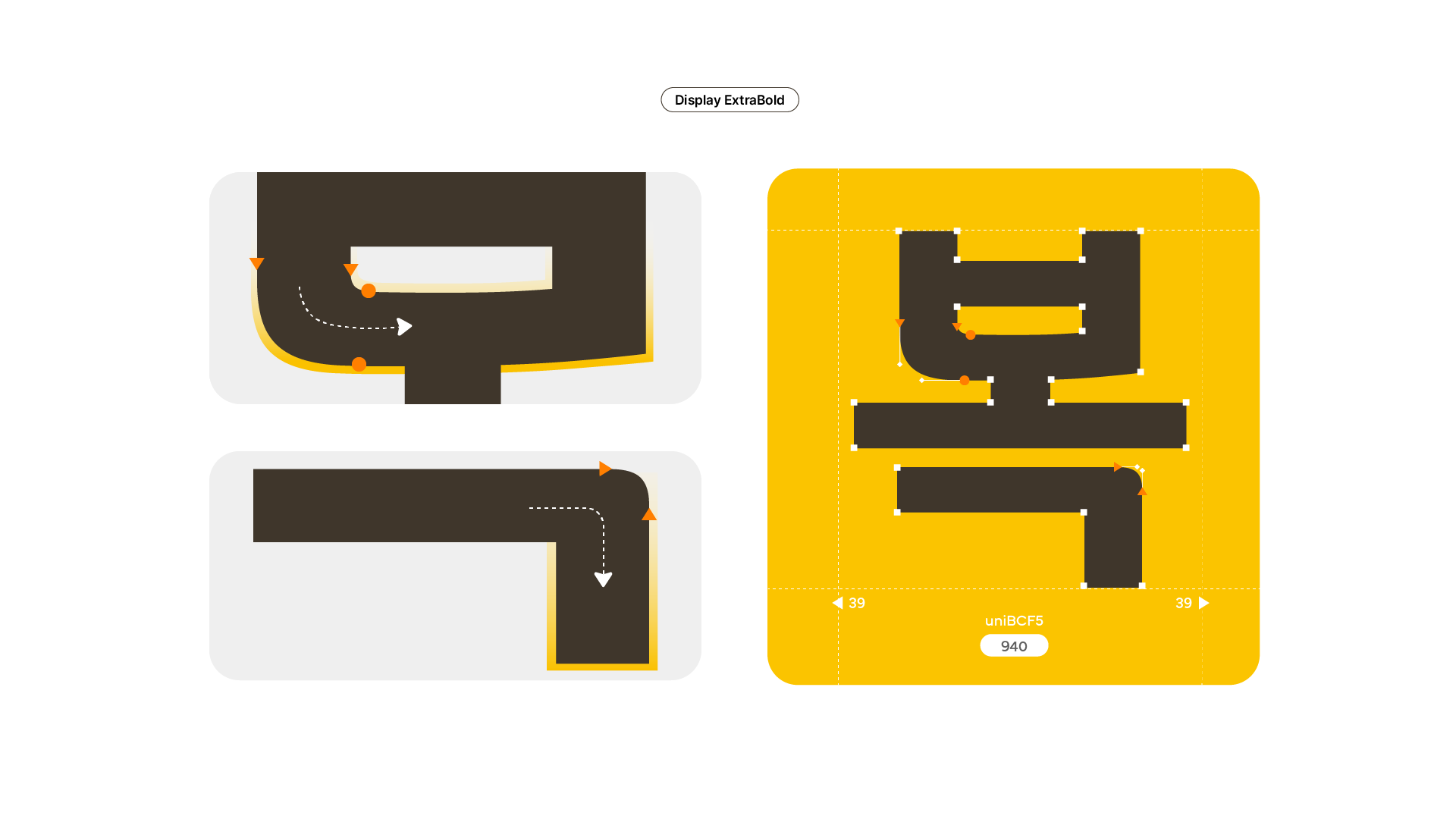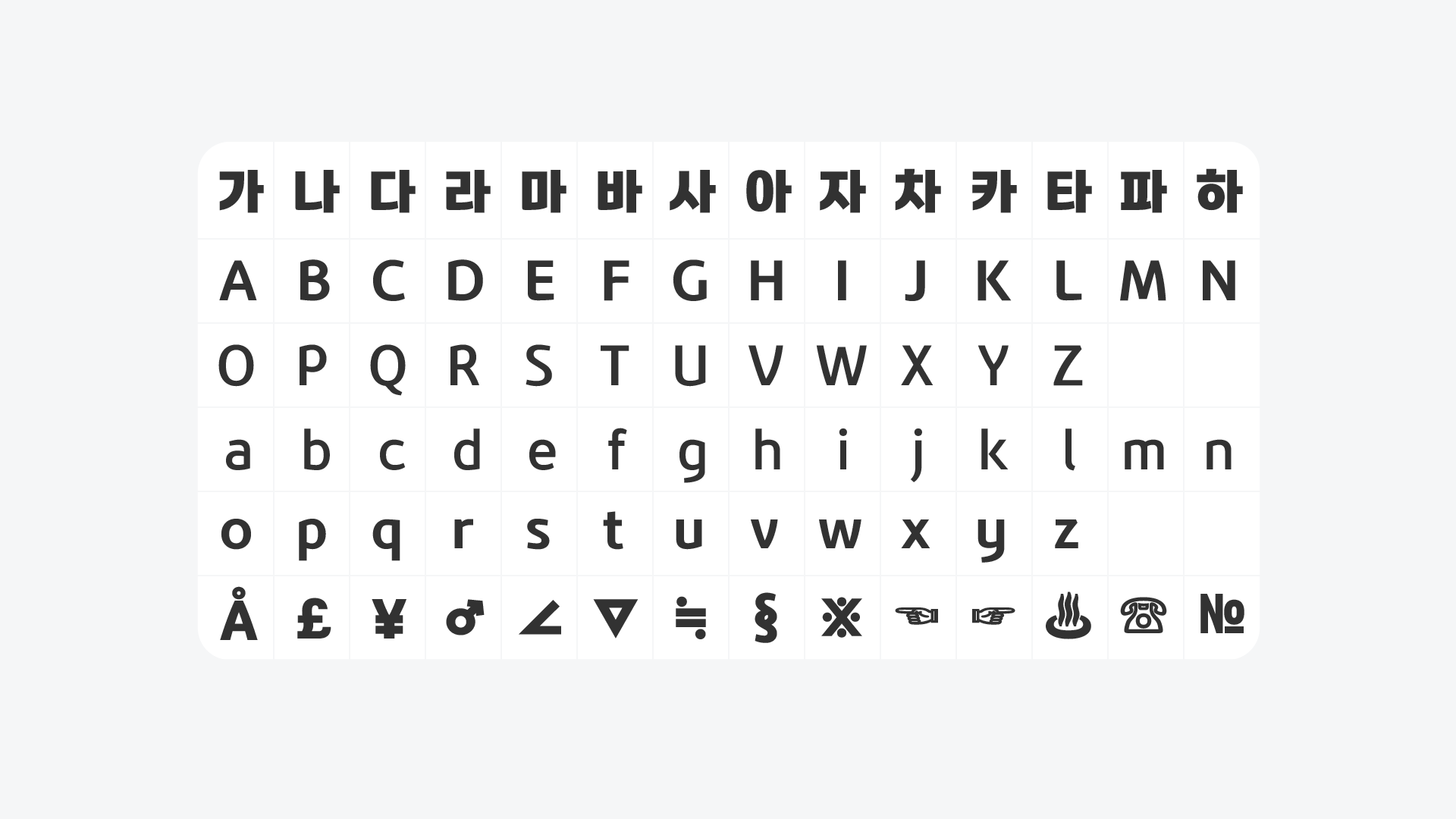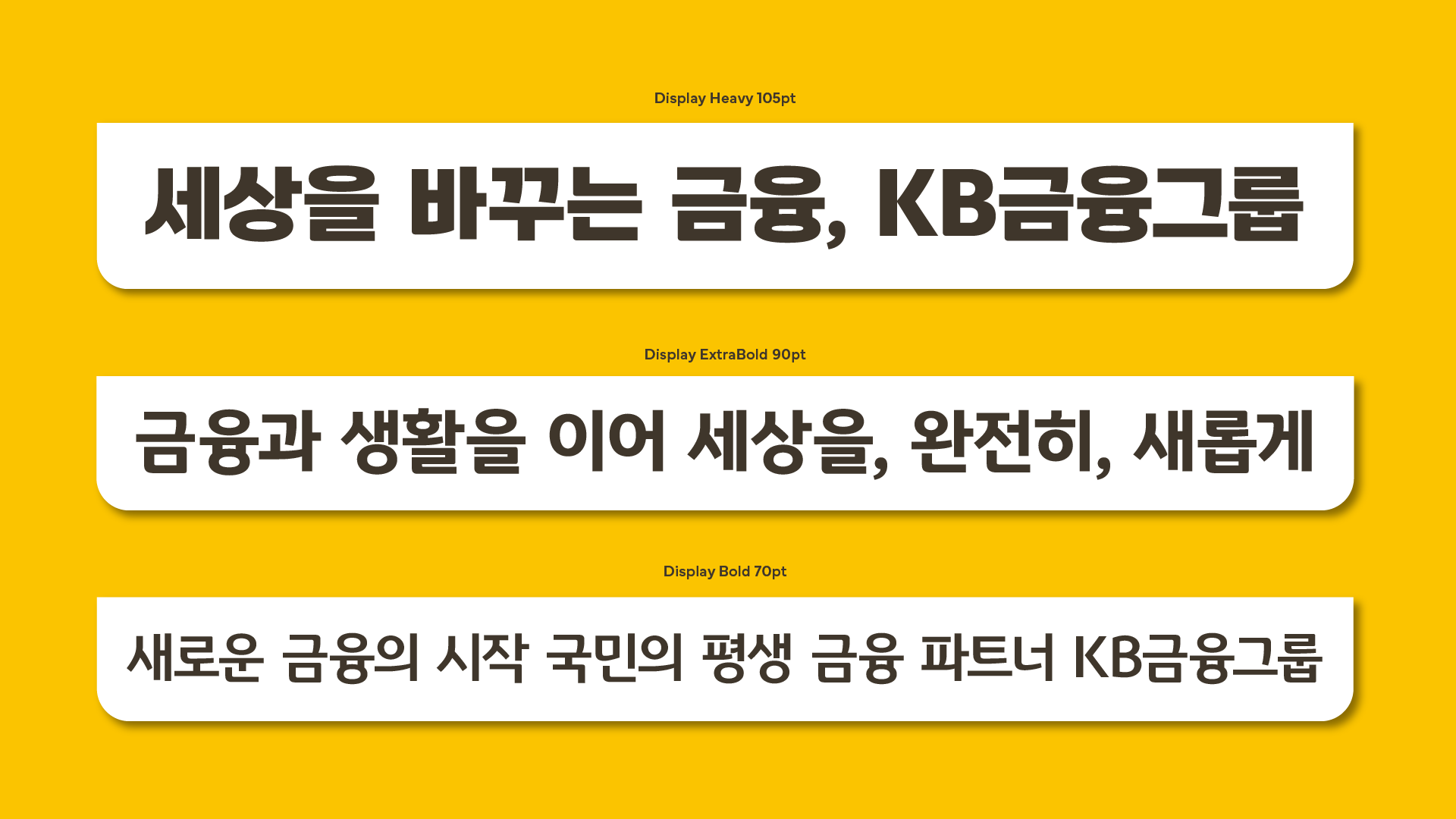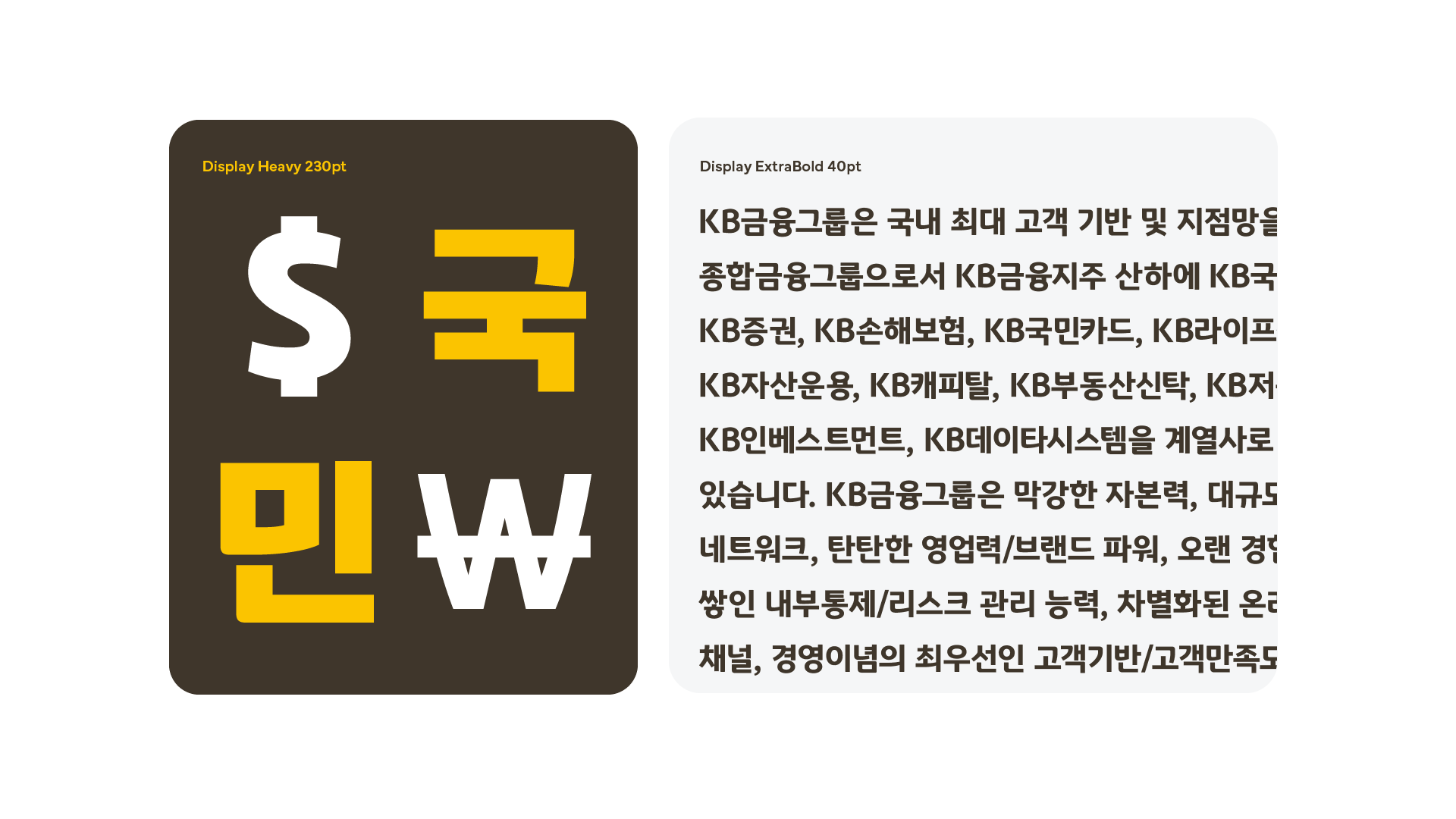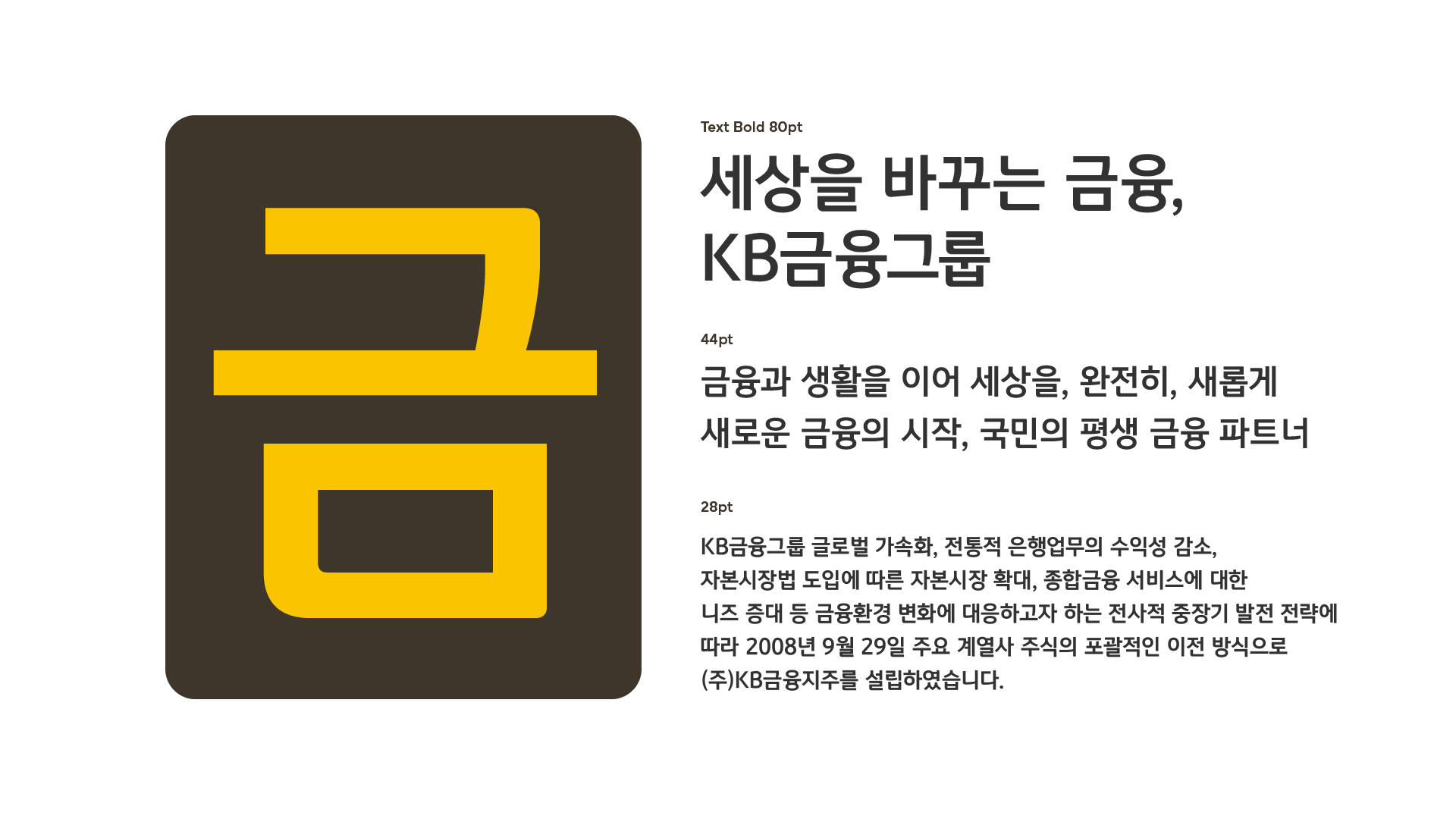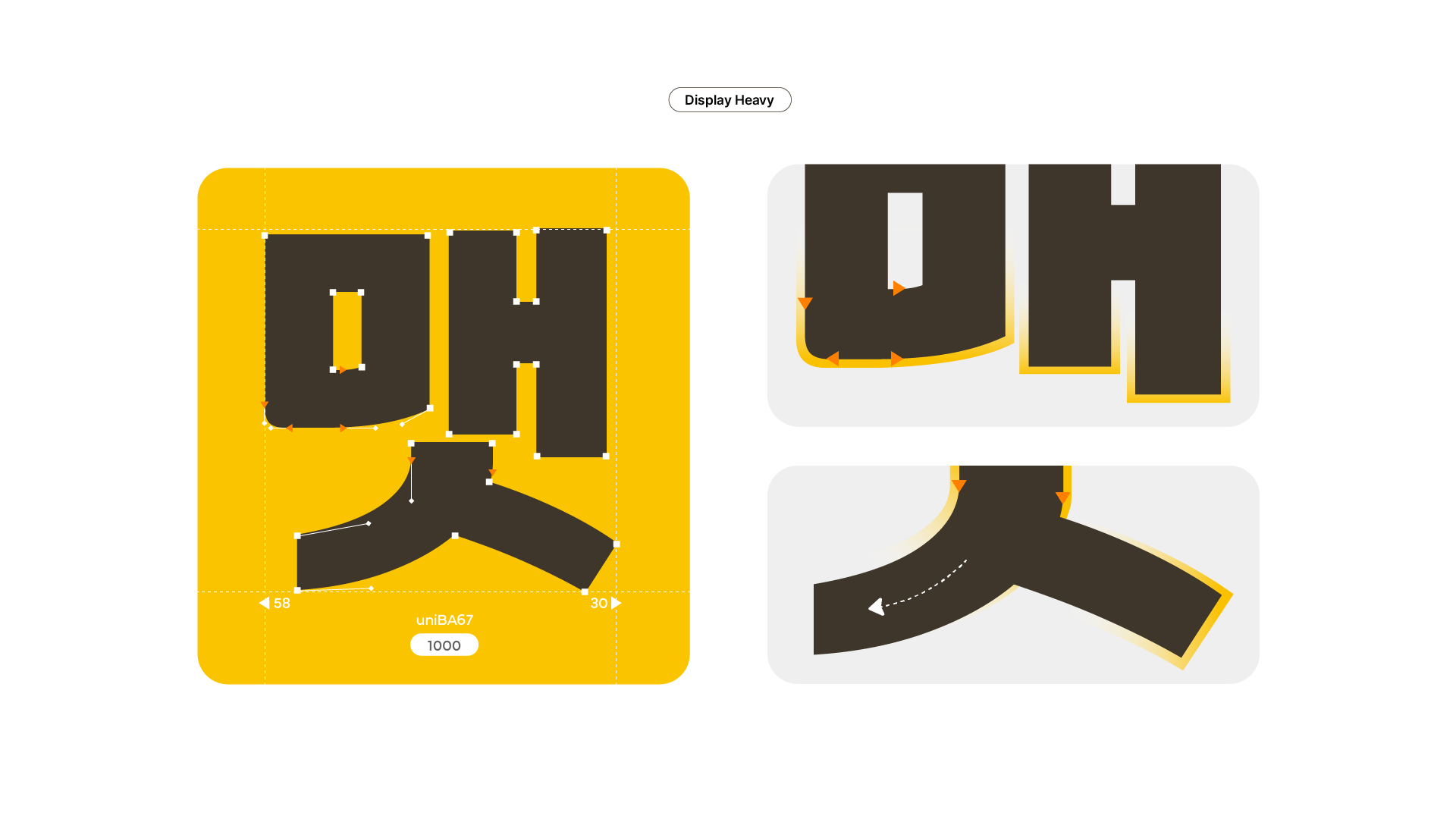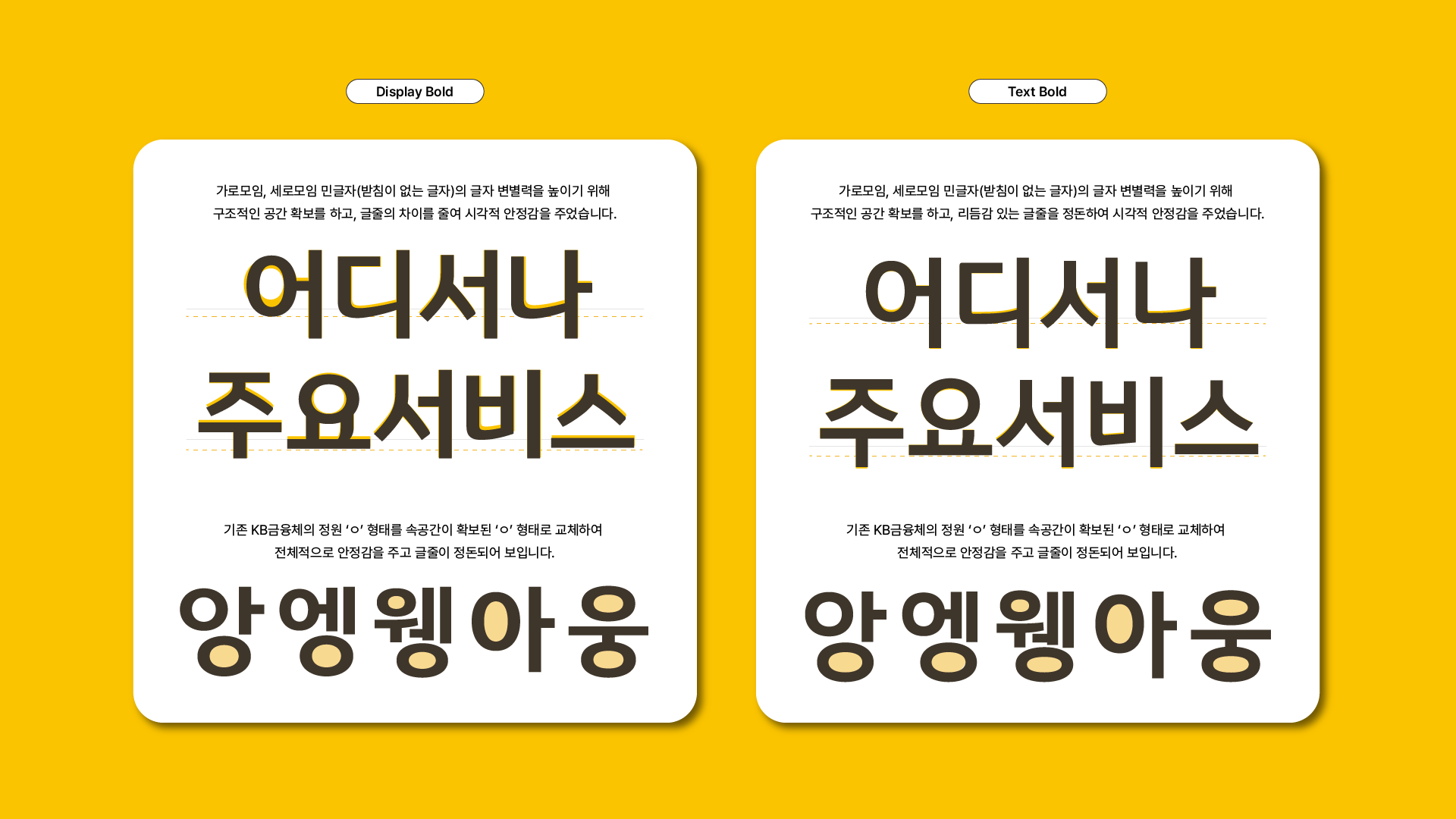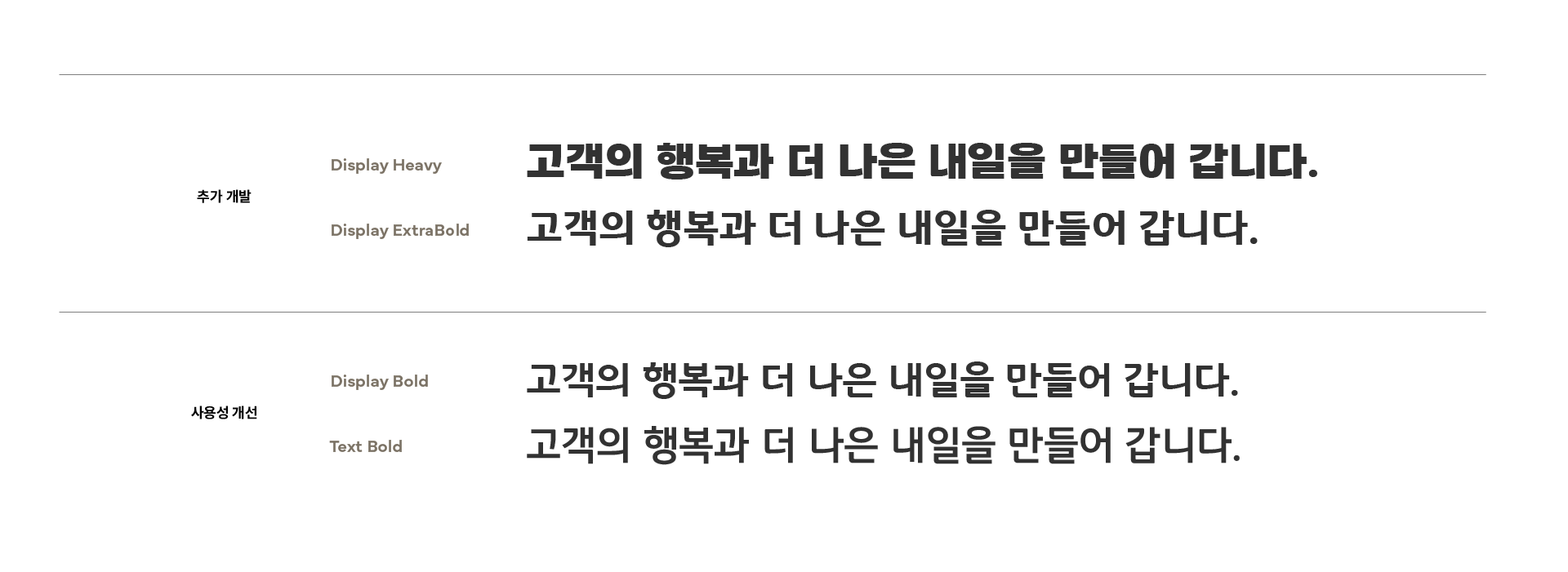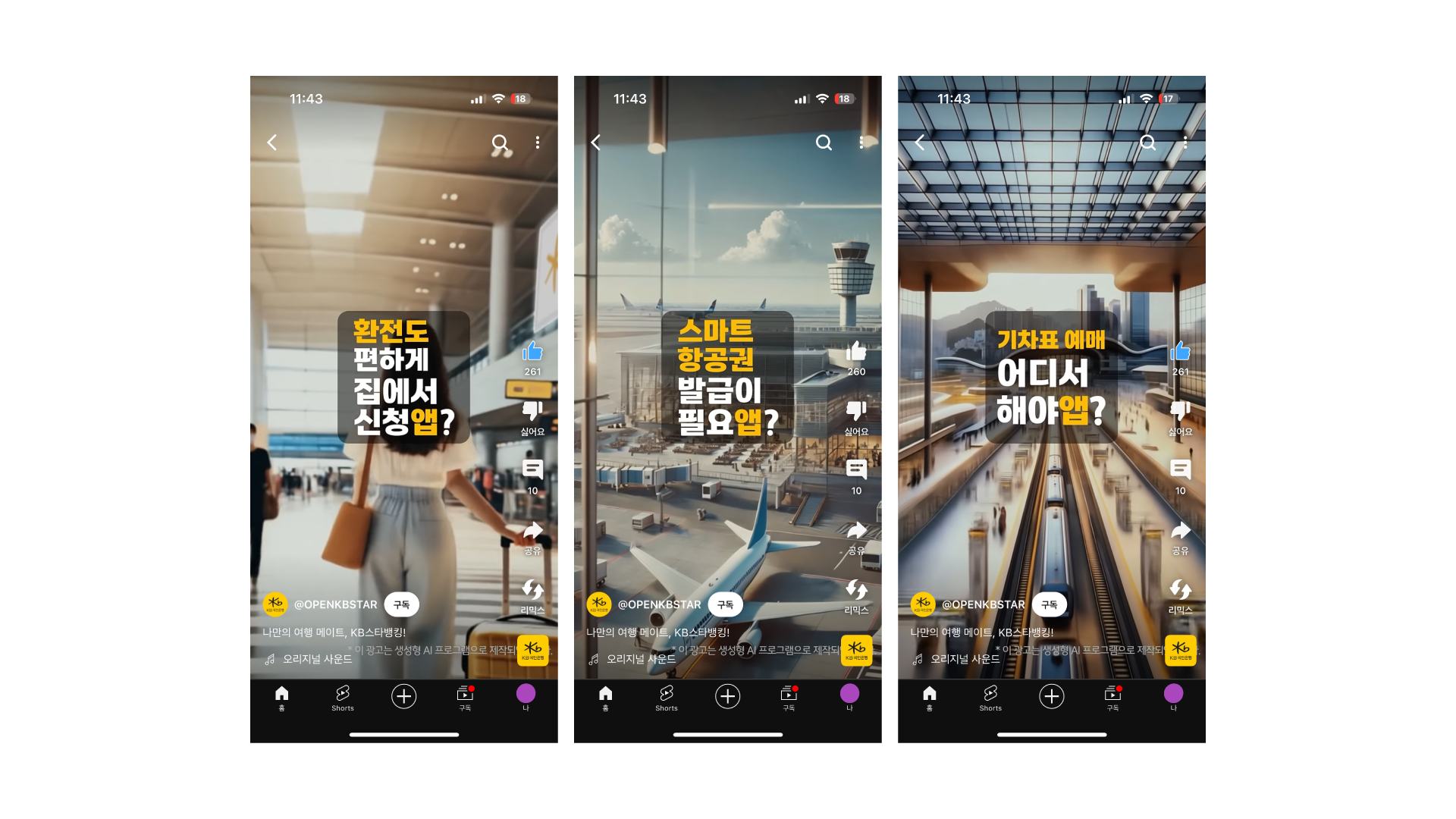
Heavy
기존 KB금융 제목체의 규칙에서 벗어나, 새로운 타이틀 서체로 탄생한 KB금융 제목체입니다. 신뢰감을 주는 직선 형태와 친근함을 전달하는 곡선 형태는 유지하면서, 진중한 기업 이미지를 새로운 방향으로 전달하기 위해 무게감 있는 꽉 찬 모듈과 굵기로 설계되었습니다.
ExtraBold
기존 KB금융 제목체의 글자 너비와 두께 구성을 바탕으로 구조와 비례를 유지하면서 굵기를 증가시킨 새로운 패밀리 서체입니다. KB금융 제목체의 세련되고 역동적인 콘셉트를 유지하되, 부드러운 곡선의 높이를 완만하게 낮추어 차분하고 진중한 느낌을 더했습니다.
Bold
KB금융 제목/본문체 Bold의 두께를 약간 수정하여 Light, Medium, Bold의 일정한 굵기 단계를 재설정하였습니다. 글자 변별력을 높이기 위해 구조적 공간을 확보하고 글줄을 정돈하여 시각적 안정감을 주었습니다.